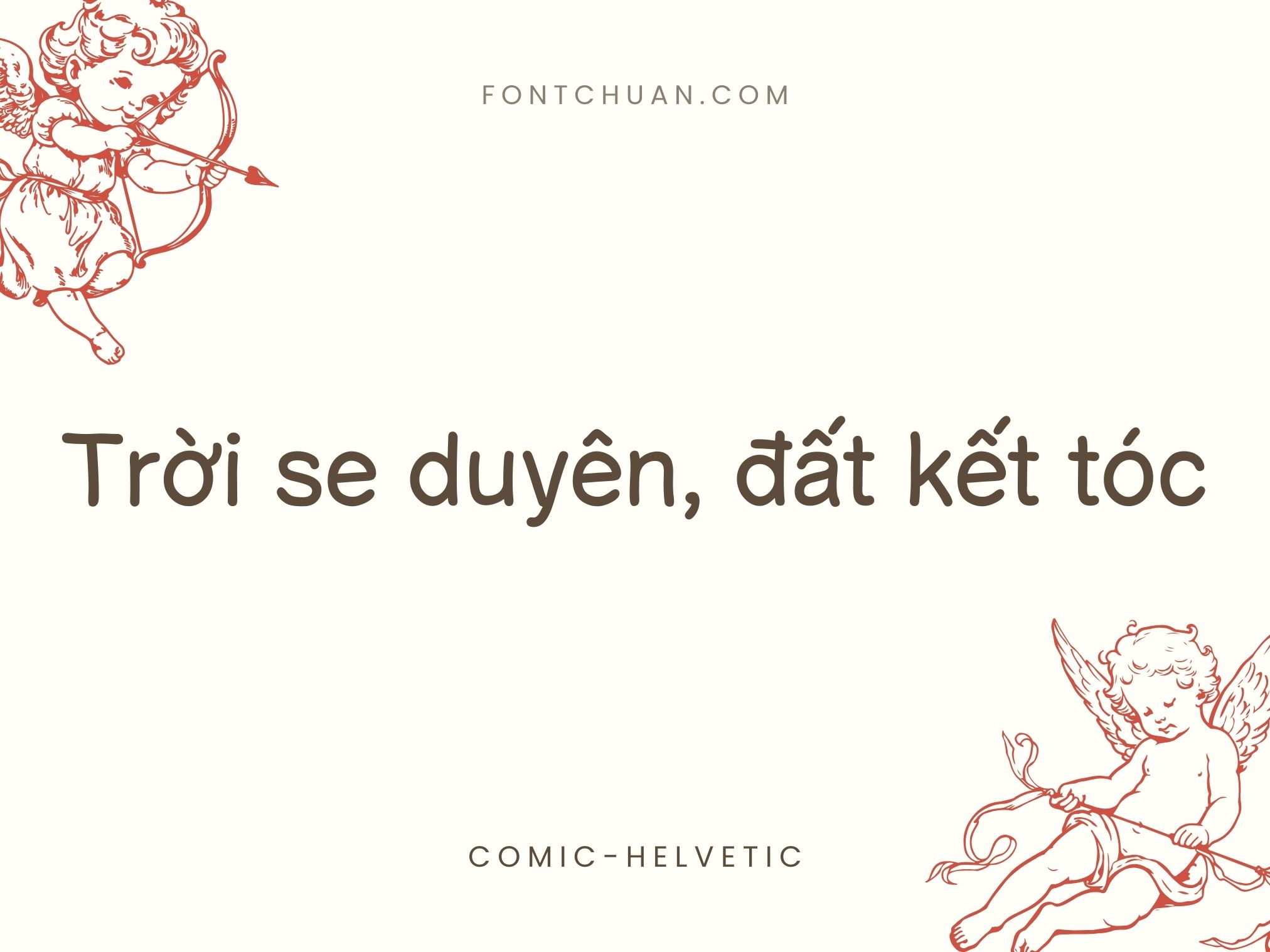
Font Comic Helvetic+ Việt Hóa
Tác giả Font: Alexander Pravdin
Comic Helvetic là một dự án thử nghiệm được thiết kế bởi Alexander Pravdin vào năm 2019, kết hợp giữa hai font chữ nổi tiếng là Comic Sans và Helvetica. Font này được tạo ra với mục đích kết hợp sự thân thiện của Comic Sans và sự chuyên nghiệp của Helvetica, tạo nên một kiểu chữ độc đáo và thú vị. Comic Helvetic bao gồm ba trọng lượng: Light, Medium và Heavy, hỗ trợ đầy đủ các ký tự Latin mở rộng và Cyrillic. Font được sưu tầm và đăng bởi thành viên của Font Chuẩn.
Với thiết kế kết hợp giữa các đường nét mềm mại và cấu trúc cân đối, Comic Helvetic tạo nên sự hài hòa giữa tính vui nhộn và nghiêm túc. Font này phù hợp cho các thiết kế như tiêu đề, poster, logo và các ấn phẩm truyền thông cần sự độc đáo và sáng tạo. Đồng thời, Comic Helvetic cũng có thể được sử dụng như một Font chữ ẩm thực, giúp các nhà hàng, quán ăn và thương hiệu thực phẩm tạo sự thân thiện, vui nhộn và nổi bật trên menu, bao bì sản phẩm hoặc các ấn phẩm quảng cáo. Ngoài ra, font vẫn được tận dụng hiệu quả trong các ngành quảng cáo, giáo dục, công nghệ và cho các sự kiện như lễ hội, sinh nhật, ngày Nhà giáo và Valentine.